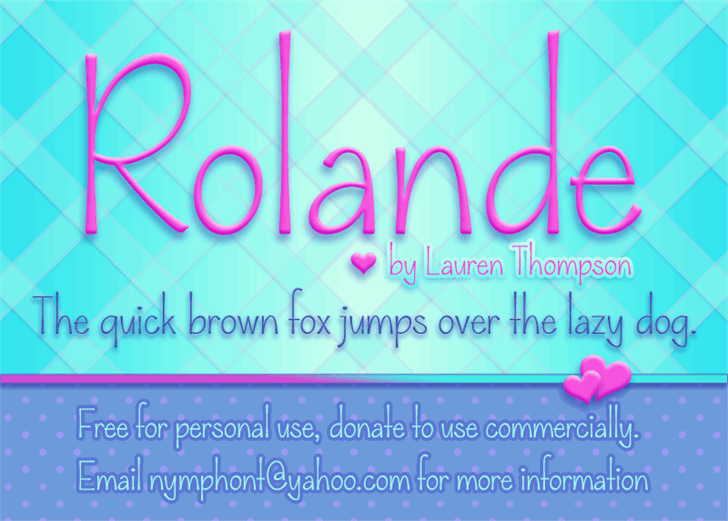
A fonte ‘Rolande Font’ é uma herança elegante do estilo de cópia à mão, criada pelo designer Hamilton para quem busca um toque delicado e pessoal em suas criações digitais. Com traços fluidos e delicados, ela oferece um suave contraste entre linhas leves e espaçadas e espaçamentos mais estreitos que resultam em uma aparência elegante e sofisticada. Proporcionando um toque de autenticidade à sua composição digital, a ‘Rolande Font’ é ideal para designers buscando introduzir personalidade na criação de logotipos, designs de websites ou até mesmo em elementos gráficos pessoais. Seja você um iniciante no campo da design gráfico ou uma experiência adicional – este estilo de fonte entrega um touch único e refinado que vai revolucionar seu projeto. Através do uso desta fonte livre para fins pessoais, mas com opção de doação para uso comercial, a Hamilton convida você a experimentar seu trabalho. Se você aprecia a beleza da ‘Rolande Font’, não hesite em entrar em contato através do email  para obter mais informações ou para explorar novos possíveis usos desta fonte incrivelmente única e sofisticada.